不少人很不注重自己写的字,写字时喜欢随心所欲,感觉这样很好看,遇到网络上流行的字体,便开始模仿。
现在学生上课时需要把笔记记在本子上,老师在课堂上传授知识,学生的速度也要跟上,课后时还要将老师,上课所讲内容好好复习一番,从而加深对知识的理解。
老师提倡学生在上课时记笔记,可以加深印象,同时锻炼学生的写字能力,老师检查作业时特别喜欢字写得好看的学生。字迹写的好看的学生,在各大考试中会给老师留下好印象,字迹的好看与否,直接影响学生的成绩。
高中女生“饺子字体”火了,字迹十分可爱,判卷老师也很喜欢
不少学生在字迹上特别重视,为了彰显自己的特征,还开创了一些独有的字体,学生在网上看到一些比较特殊的,适合自己写的字,基本上都会学习,由于高中生把看到的网络字体融入在生活中,写出来的字赢得了老师的称赞。
很多学生很好奇,看到这种字体之后纷纷开始模仿,这位女生写的字体,被大家称为“饺子字体”。字体特点是看起来圆圆滚滚,很可爱,整个字像圆滚滚的球一样,深得学生喜欢。
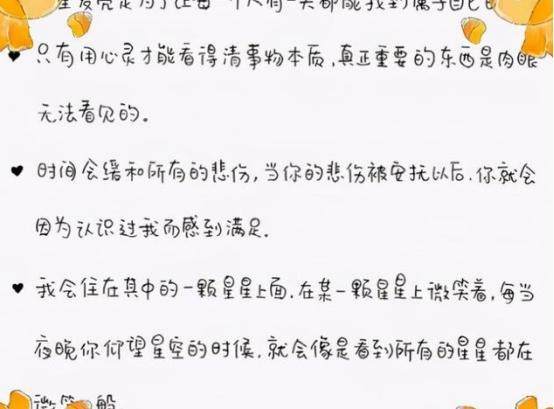
尤其女生对于这种字体,没有任何抵抗力,不管是写字或在生活中
尤其女生对于这种字体,没有任何抵抗力,不管是写字或在生活中都愿意写这种字体,字迹很可爱,能写出这样的字体,不是一件容易的事,需要下很多功夫。
饺子字体的特征则是,竖不是竖横不是横,好像是一个又一个的小饺子,每个字看起来很饱满又很圆润,老师看到这种字体觉得很美观。
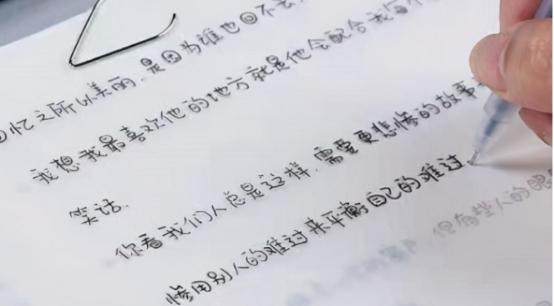
饺子字体和奶酪字体的差距?学生应写哪种字体?
两者之间有相同的地方,同样也有不一样的地方,首先两个字体同属于可爱类,不过每个字体特征不一样,有属于自己的特点。
奶酪字体比较工整,最后一笔上具有鲜明的特征,每一个字都有点弯曲,整个字看起来圆润。
这两种字体难易程度不一样,奶酪字体比较好写,现在网络上流行字体越来越多,比如深受大家欢迎的衡水字体,学生看到了哪些字体,喜欢便去学习。
学生选择哪种字体?主要在于学生写哪种字体比较容易,不过老师青睐的字体。则是看起来简单明了,笔画顺序工整的字体。
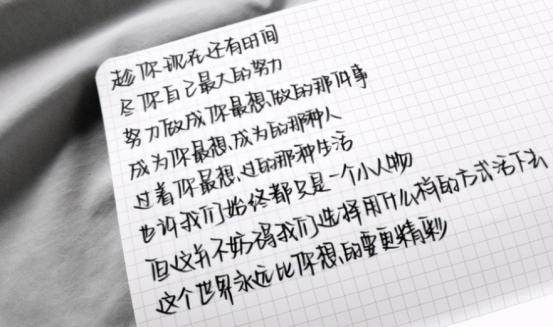
学生要注意,写字时不要追求美观而忽了其他,如果写的字是错别字,老师不会打高分,决定好好写字,要静下心来一笔一划完成,哪怕写出来的楷书,同样很漂亮,不一定非要追求网络上流行的字体。
个人觉得学生写出来的字,首先要能认识,其次写出来的字要工整,如果写出来的字老师都认不出来,那么写的字就有点失败。学生可以根据自己平时写字习惯,选择最为适合自己的字体,并且好好进行练习,相信一定能写出一手漂亮的字。
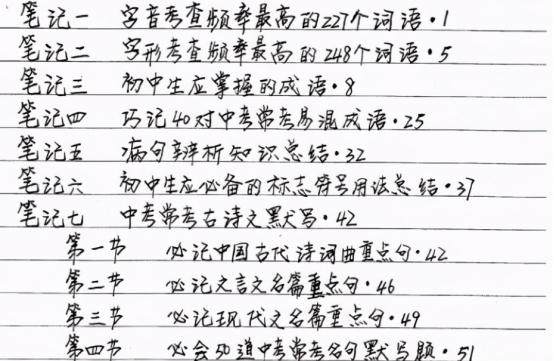
学生比较常见的三种字体,学霸都喜欢学习
对学生来说写得一手好字真的很重要,尤其是文科学习,字迹好的学生和字迹差的学生,试卷上分数会有差距,老师进行评分时,肯定愿意给字写的好看的学生高分。即便是学霸,忍不住纷纷去学习,不知道你所写的字是否在其中。
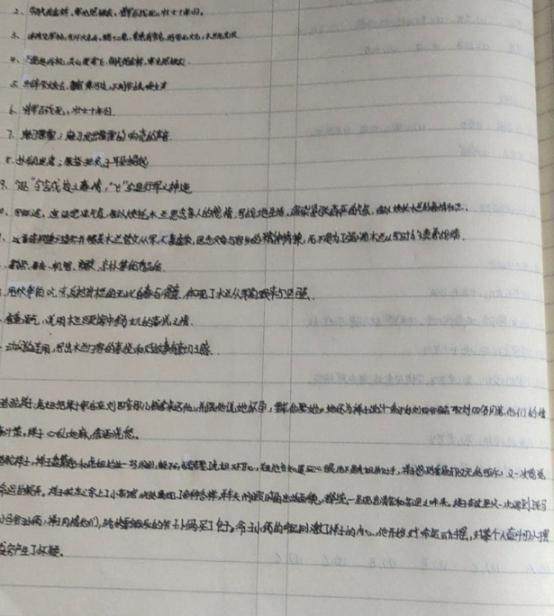
蚂蚁式字体:有不少人写字时把字写得比较小,远远看上去好像是很多蚂蚁爬在课本上,分辨时不太好看,这种蚂蚁式字体看起来特别费劲,再加上学生写作,如果距离本子太近,确实很伤眼睛。
写的字一定要端正,看起来美观,不要嫌弃别人说自己写的字不好看,只要我们去改正,总能写出好看的字,如果一直坚持写蚂蚁式字体,很容易让学生近视,老师看到这样的字体估计会抓狂,要一个字一个字地去看,生怕错过了哪个对的答案。
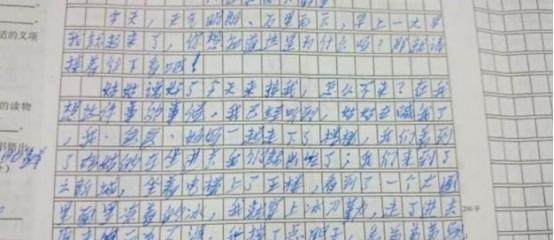
草书式字体:写字时容易龙飞凤舞,草书是很多学生经常犯的错误,字迹十分潦草,考试时漫不经心的写字,由自己随心所来写出来的字,自己认识老师不认识,这种草书式字体,有种自由放荡不羁的感觉,并不值得学习。
学霸式的字体:能写出这种字体的学生一般成绩都不是很差,给人一种学霸的感觉,观察班级里学得好的学生,写出来的字体基本上比较统一,字写的好看,阅卷老师会认为这个学生成绩比较好,即便成绩很一般,但老师一看到学霸式的字体,总忍不住打高分。
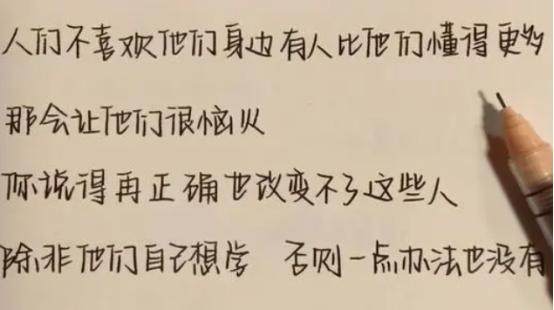
学生在考试时要注意字体,不仅要写的工整,要写的规矩,字迹潦草会给学生带来不好的影响,与此同时答题时不要出现错别字,也不要出现字写错了后用笔去涂抹,不然看起来很难看。